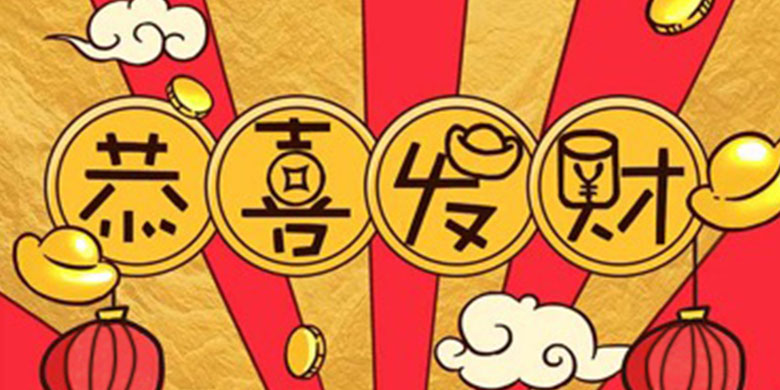
品牌:方正手迹设计师:高宇发行时间:2018字库编码:大陆简体(GB2312-80)分类:创意书写字体属性:精品字
恭喜发财是一款添加个元素的创意字体,添加了元宝、爆竹、铜钱、中国结等新年元素进去,让人一眼看去就感觉到了过年的喜庆气氛。非常适用于新年相关的书刊、品牌广告和产品包装设计,以及社交网络的个性化用字。